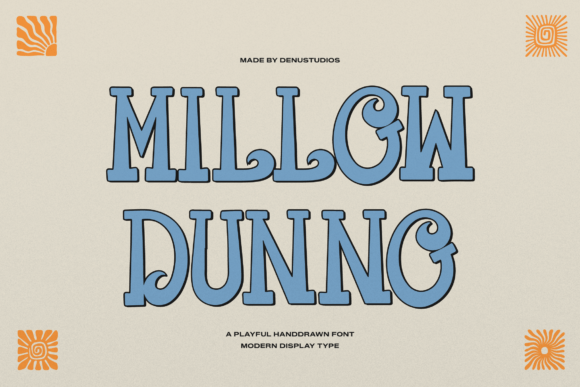
Millow Dunno
適切なデザイン要素を見つけるのは難しい場合がありますが、Millow Dunnoは作品を即座に引き立てる優れたコレクションを提供します。
POD(オンデマンド印刷)製品、結婚式の招待状、またはソーシャルメディアのグラフィックを作成している場合でも、Millow Dunnoは理想的です。